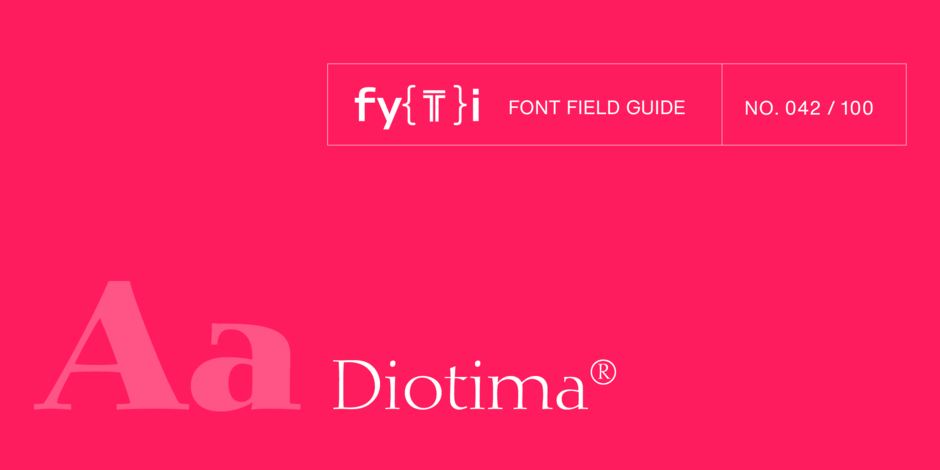
Diotima Classic® Fuente Guía de Campo
FUNDICIÓN: Linotype
DISEÑADOR: Gudrun Zapf von Hesse, Akira Kobayashi
CLASIFICACIÓN: Didone
Buenas prácticas
Diotima Classic Regular y Bold son inconfundibles y muy legibles en tamaños de texto. Diotima Classic Light también puede ser una opción excelente para bloques cortos de texto. Junto con los pesos Bold y Heavy, crea titulares llamativos.
Familia
Diotima Classic es una familia de cuatro pesos, cada uno con un diseño cursivo complementario.
- La letra de Von Hesse sirvió de base para los diseños en cursiva.
- Diotima es un término de la antigua Grecia, y se traduce como "honrado por Dios".
- Las formas de las letras de Diotima Classic son más armoniosas y equilibradas que las del diseño original.
Raíces
Gudrun Zapf von Hesse empezó a diseñar la Diotima original en 1939, cuando era encuadernadora. Entre 1951 y 1953, D. Stempel AG lanzó el diseño como familia tipográfica de metal para composición manual. En 2008, Akira Kobayashi, director tipográfico de Linotype, y von Hesse colaboraron para revivir y reinterpretar Diotima tanto para texto como para tipografía de visualización. El resultado es Diotima Classic.
Legibilidad
Aunque decorativos, los caracteres de Diotima Classic son muy legibles tanto en texto como en tamaños de visualización, en pantalla y en papel.
Cómo detectar Diotima
Opciones alternativas
Maridaje perfecto